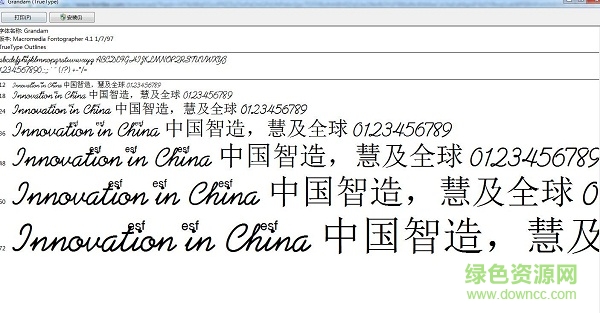
grandam font
grandam字體是一款精美優(yōu)美的英文字體,該字體筆形富于變化,線條勾勒細(xì)致,給人的感覺浪漫優(yōu)雅,適合用在書信設(shè)計(jì)、影視海報(bào)、平面設(shè)計(jì)、裝飾裝幀等領(lǐng)域,歡迎有需要者前來下載!
grandam font